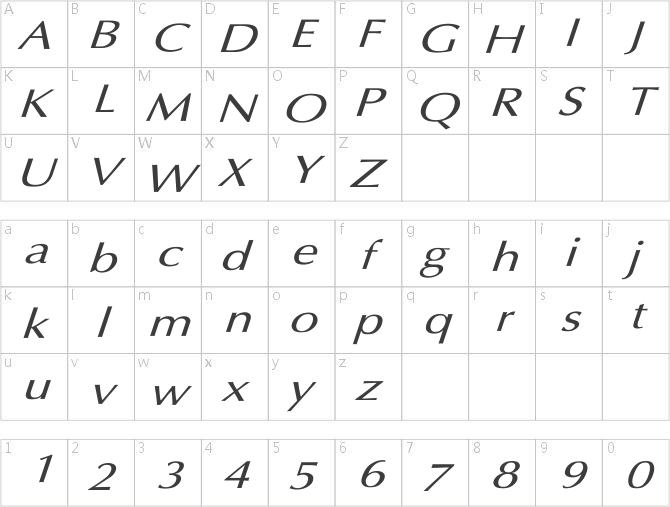
Optima-Italic-Wd-Italic 詳情頁
Optima-Italic-Wd-Italic字體字庫是一款讓人賞心悅目、百看不厭的英文字體,適合各類廣告和產(chǎn)品包裝設(shè)計應(yīng)用,字體大小0.15MB,格式為ttf字體,上傳用戶是昊天金誠,作者/版權(quán)方為未知